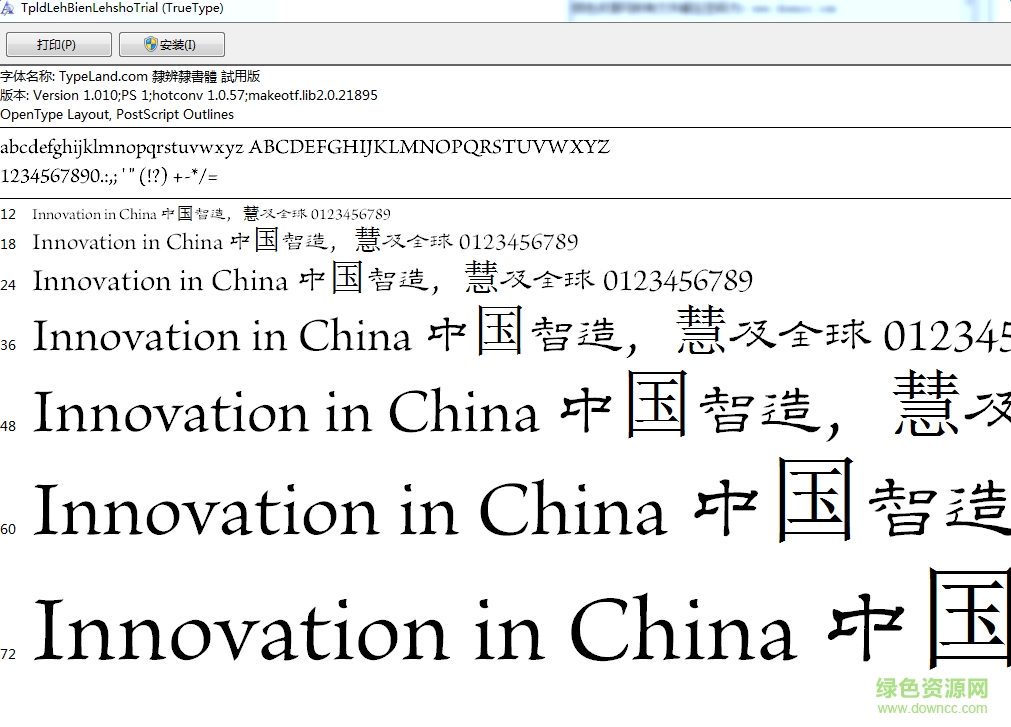
typeland隸辨隸書(shū)體
隸辨隸書(shū)體是一款古典創(chuàng)意類(lèi)字體軟件,隸辨隸書(shū)體字體大小不一,看似凌亂卻透露著一絲藝術(shù)的氣息,粗細(xì)相間,十分優(yōu)雅,還有更多類(lèi)似好看字體歡迎來(lái)綠色資源網(wǎng)下載體驗(yàn)!
隸辨隸書(shū)體是一款應(yīng)用于藝術(shù)設(shè)計(jì)方面的簡(jiǎn)體中文字體,該字體筆畫(huà)粗壯,尾部的甩尾有力且有豐富的筆觸細(xì)節(jié),大字效果突出且引人注目;并且最大程度還原作者書(shū)寫(xiě)字形,細(xì)節(jié)表現(xiàn)完整,且字庫(kù)完整,可以廣泛應(yīng)用于名片設(shè)計(jì)、新聞媒體、宣傳海報(bào)、ppt、影視制作以及內(nèi)容用字等領(lǐng)域。
該字體筆畫(huà)粗細(xì)不一,字體大小不盡相同,非常的古典有創(chuàng)意,整體效果十分非主流,盡顯書(shū)法大師的魅力,用來(lái)耍酷再合適不過(guò)了!